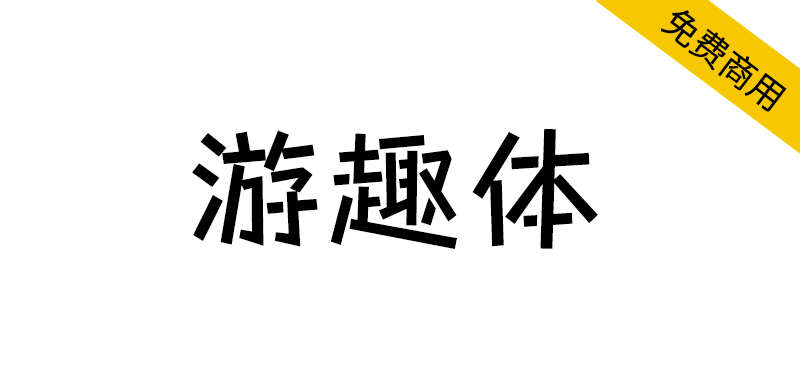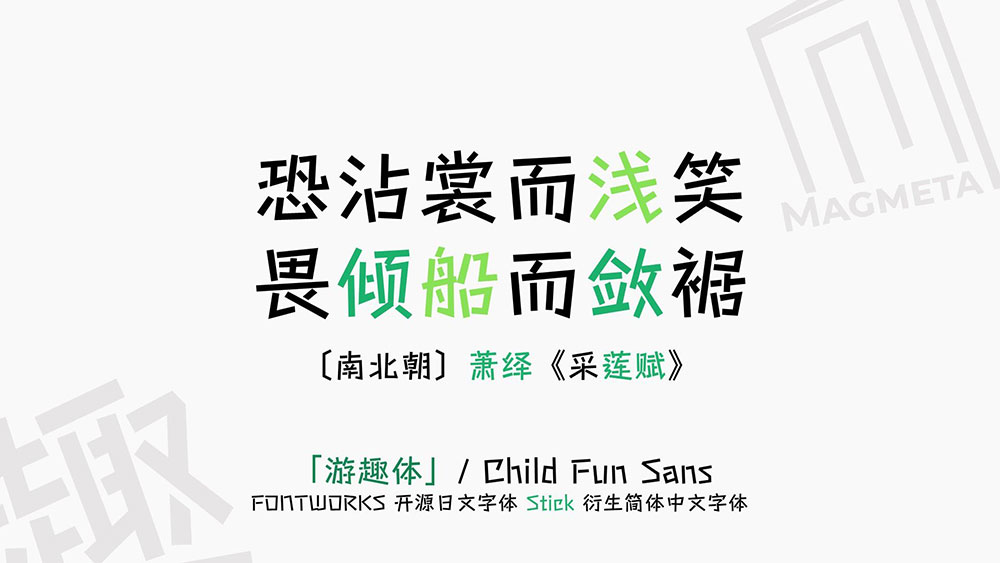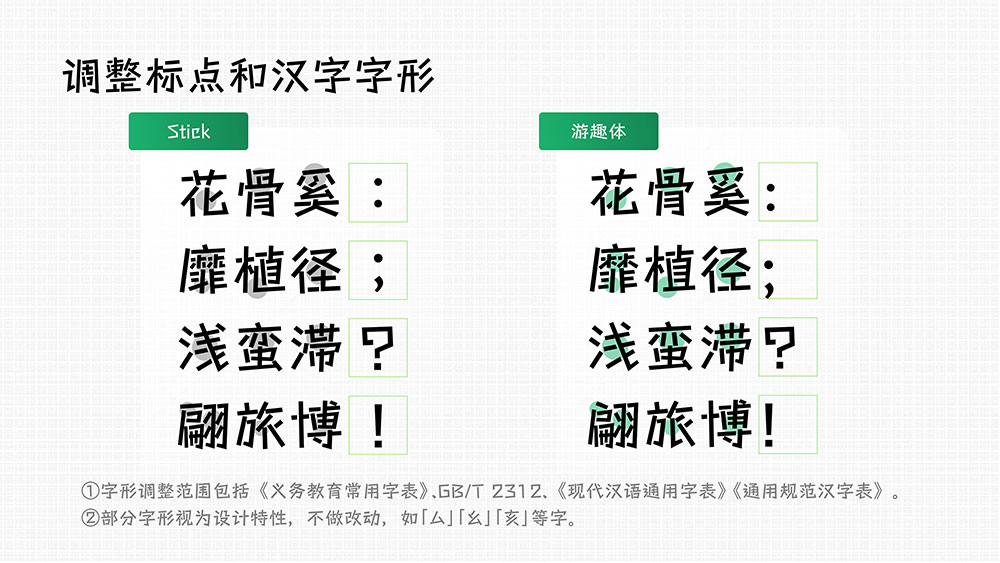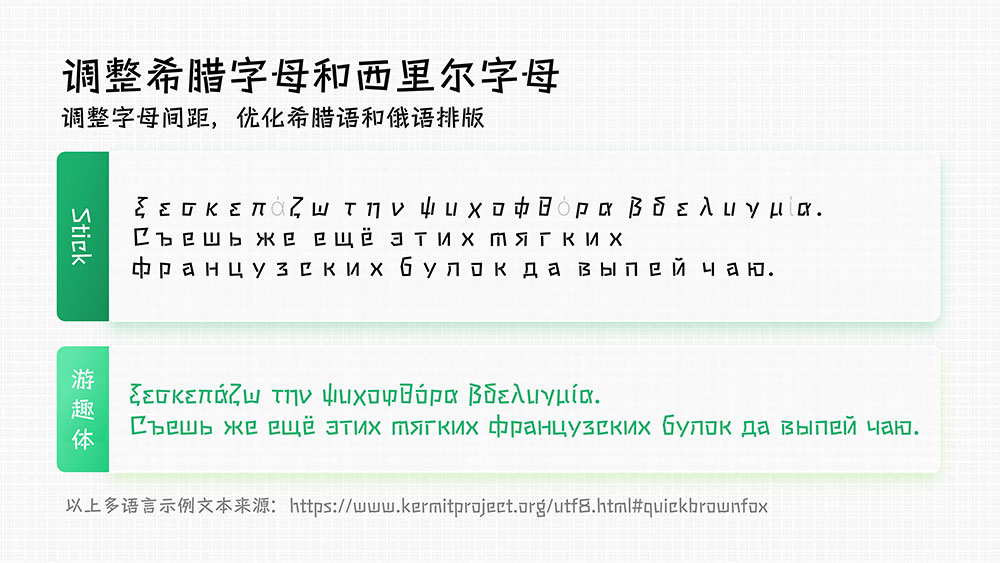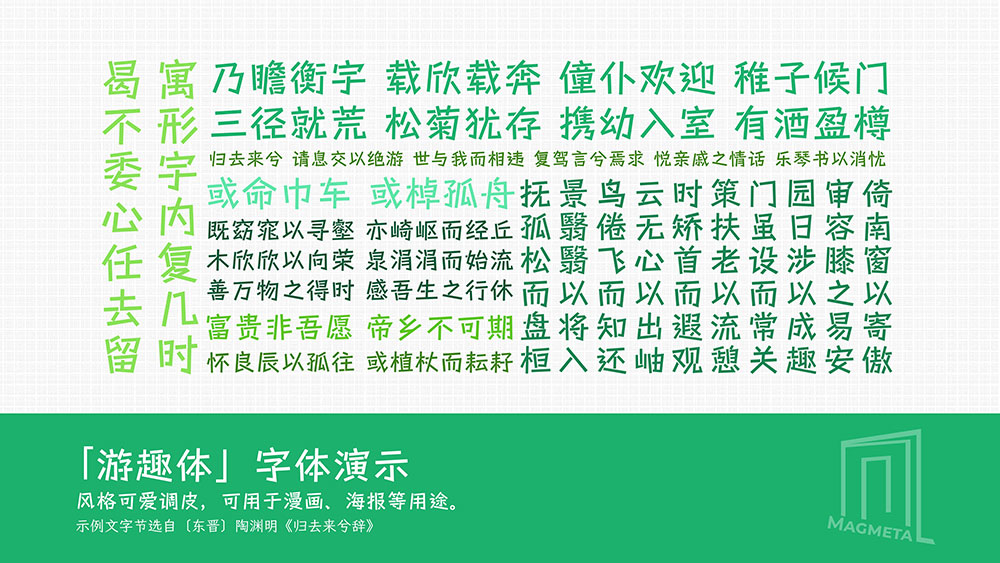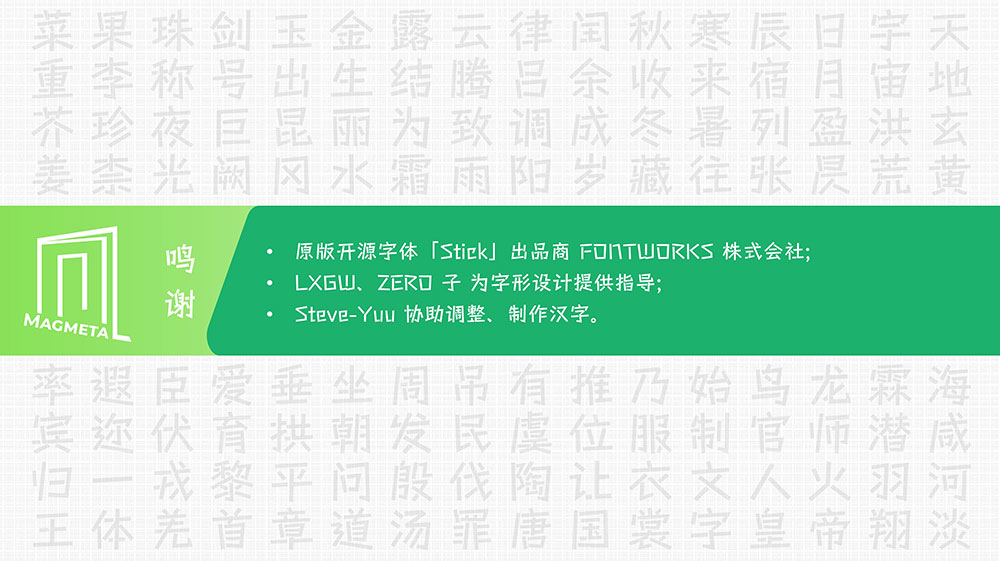
游趣体因笔形像笔杆一样以直线设计,而被视为一款既可爱调皮,亦有田园写意风格的字体,本人基于 Fontworks 出品的日文字体ステッキ / Stick 扩充、调整字形,并编辑、适当增加 OpenType 特性,以满足简体中文的使用需求。
繁体部分:由于该字体目前定位仍以简体为主,目前无对原字体包含的繁体部分增补及修改的计划
注意事项:本人并不是专业的设计师,并未考虑设计美感,所以看起来可能略丑,补进去的字与原版可能略有违和感,且在新补字符中部分字的轮廓曲线会有毛刺。此外由于时间仓促,并没有多余的时间细修,部分字的部件拼接会很生硬。在补齐 GB/T 2312-1980 前,此字体将出现一定的缺字可能。